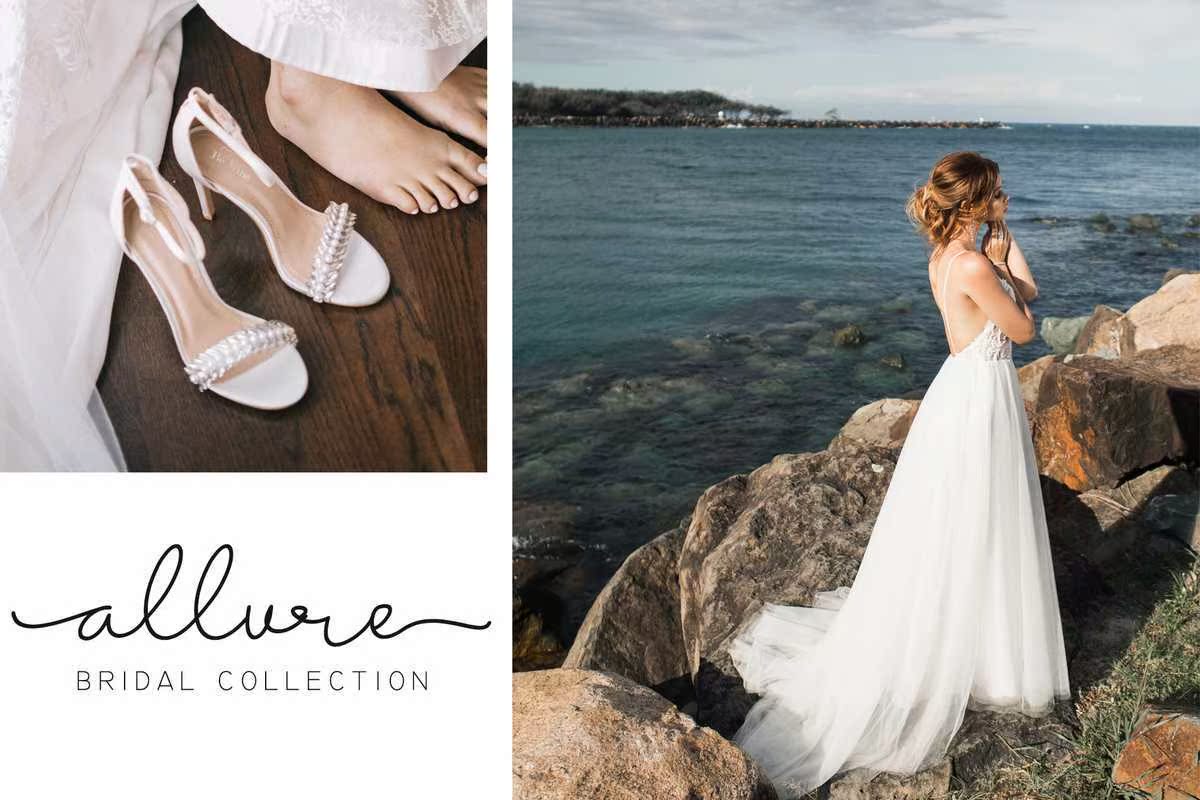
Battilla是手写的单字字体,带有Legant和Beautiful的外观。Battilla将寻找PerfectforLegant徽标、婚礼统计表、海报、引用、短文本、品牌、网络、图形设计和任何其他需要手写的项目。Battilla是手写的单字字体,带有Legant和Beautiful的外观。Battilla将寻找PerfectforLegant徽标、婚礼统计表、海报,报价、短文本、品牌、网页、图形设计和任何其他需要手写的项目。